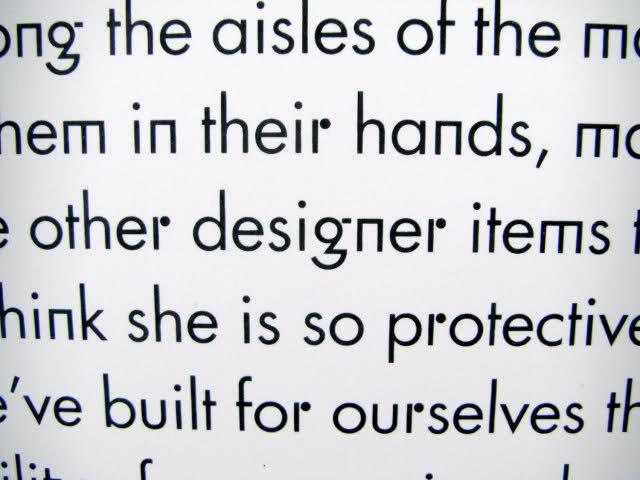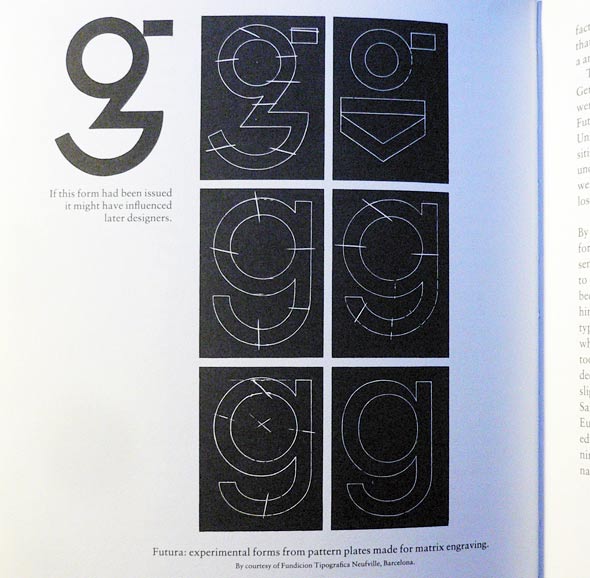
Kennt jemand diese Schrift?
Gefunden in Vilnius, Litauen in einer Ausstellung.
Erinnert etwas an die Futura, wobie die Buchstaben m, n, g oder r dann doch sehr, sehr eigen sind.
irgendeine Hardcorevariante der Futura, nehme ich an.
Vielleicht eine der alternativen Formen bei der Dessau?
Edith meint: erst lesen, dann schreiben. Entschuldigung. Immerhin gäbe es bei der Dessau die von Paschulke bevorzugte rennersche Form.
Geht die oben gezeigte g-Form nun auf Renner zurück
Soweit ich weiß, ja. Als Beleg zur Hand habe ich gerade Walter Tracy, Letters of Credit, S. 94; da sind Originalzeichnungen («pattern plates») von insgesamt sechs (teilweise «experimental») Futura-"g"s abgebildet, u.a. genau dieses.
Ein bißchen »overstyled« sind diese Formen schon, die es nicht ins »final design« geschafft haben, und sicher wäre die Futura mit diesen Formen eine Fußnote der Schriftgestaltung geworden und nicht so ein Erfolg. Aber ein zweistöckiges g zur Futura wäre z. B. schon nett, und das obige ist ja mal wirklich originell.